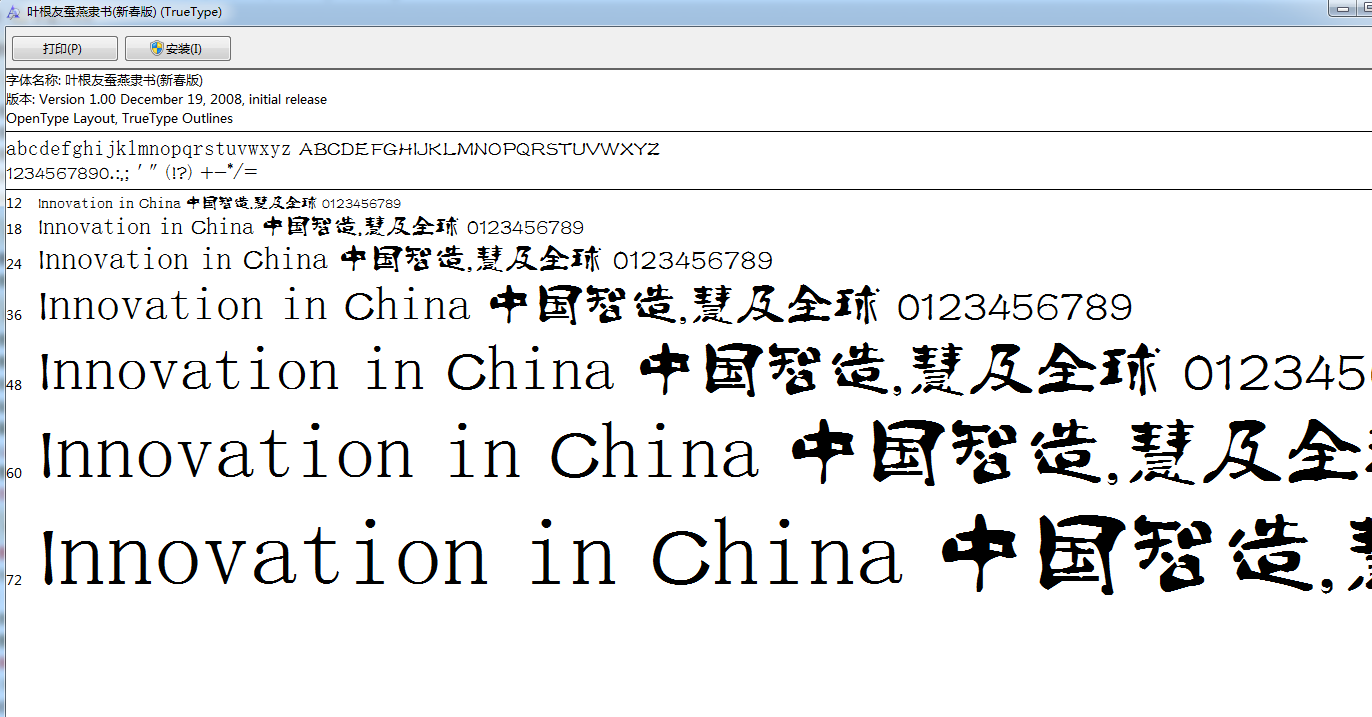
葉根友蠶燕隸書(shū)是一款具有隸書(shū)的傳統(tǒng)風(fēng)格和現(xiàn)代書(shū)法之結(jié)合體創(chuàng)新字體,賦予字體內(nèi)在的遒勁之美,圓潤(rùn)而富有質(zhì)感,特點(diǎn)鮮明,讓人看后過(guò)目不忘,為葉根友系列字體最受歡迎字型之一。將隸書(shū)的蠶頭燕尾之風(fēng)格包容于字里行間,用現(xiàn)代的創(chuàng)作思維去于古代書(shū)法對(duì)話,正所謂師古而不泥古,在葉根友認(rèn)為,所有書(shū)法創(chuàng)新也好,創(chuàng)作也罷,均是建立在古人的肩膀上去思考,但是不能一味的去模仿古人,而是要有自己的風(fēng)格特征,正如這款葉根友蠶燕隸書(shū)字體作品而言,每個(gè)字的起筆和運(yùn)筆都流露出一種書(shū)寫(xiě)者當(dāng)時(shí)的真實(shí)心境,這款字體是在江蘇常州創(chuàng)作的,歷史四個(gè)月的書(shū)寫(xiě)過(guò)程,每次寫(xiě)完不滿意的一律扔掉,前后大約有些字寫(xiě)了八到十次之多。